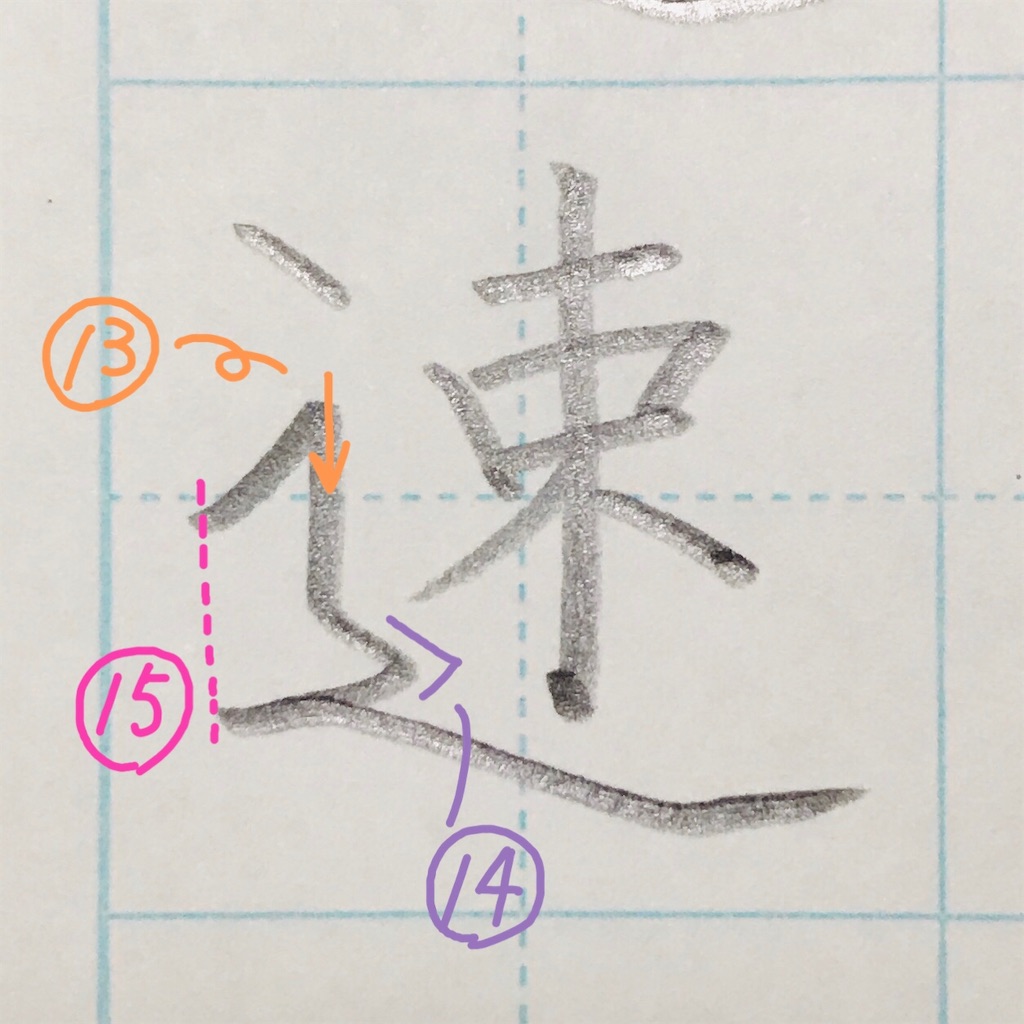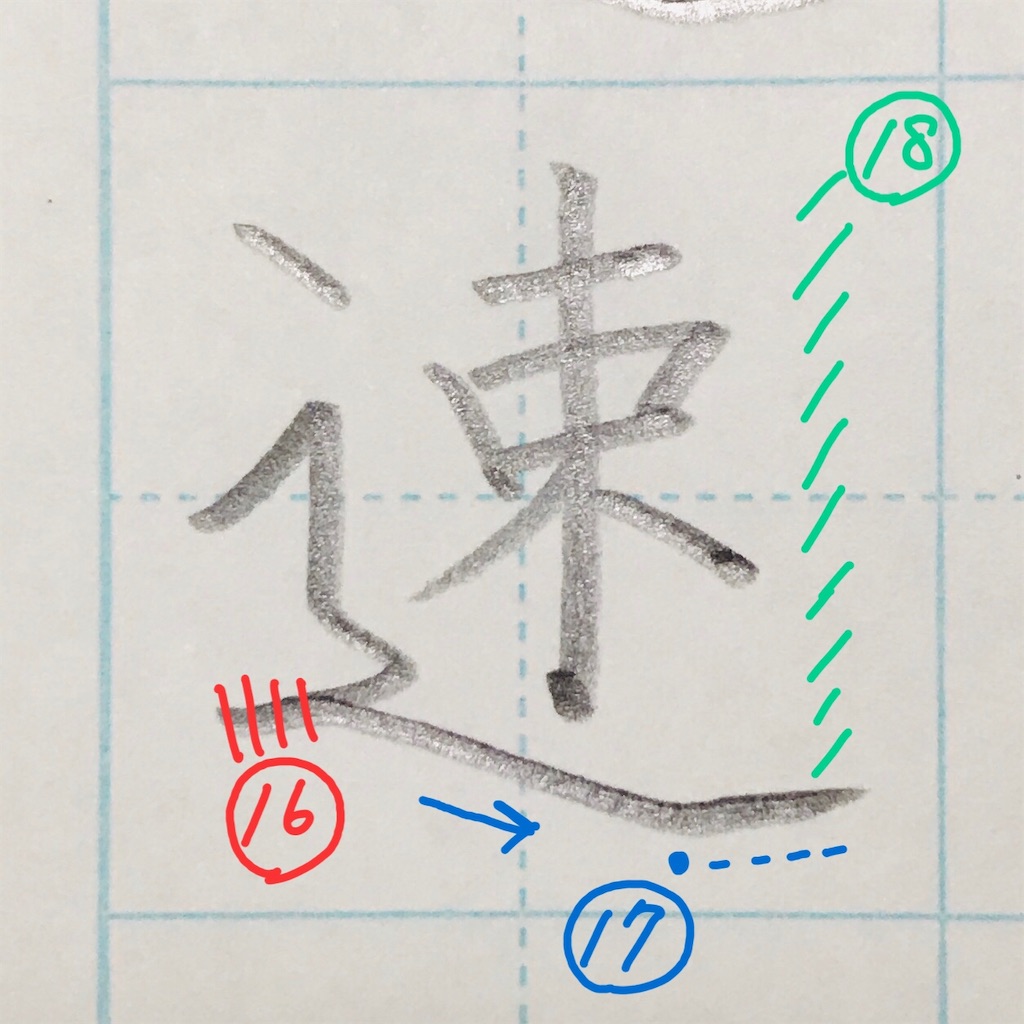
「速」のきれいな書き方。
今回は「速」のきれいな書き方を解説します。
「速」の見本
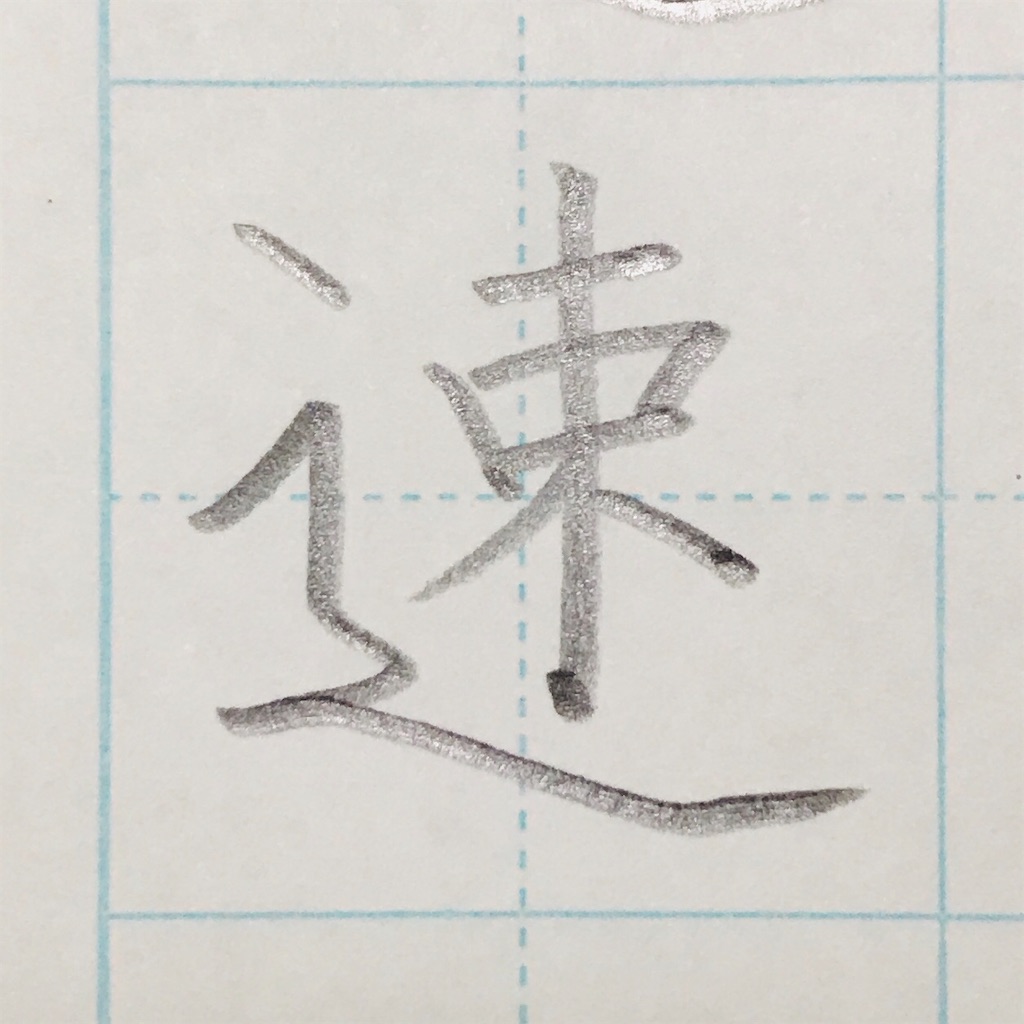
「速」の書き順
10画です。
「速」のポイント
①スタートは中心より少し左から。
②「口」の縦画はキュっと内へ入れる。
③横画は右上がりに揃える。
④間を等しく。
⑤「縦」と「横」を出す。
⑥まっすぐ。「束」部分の中心に。
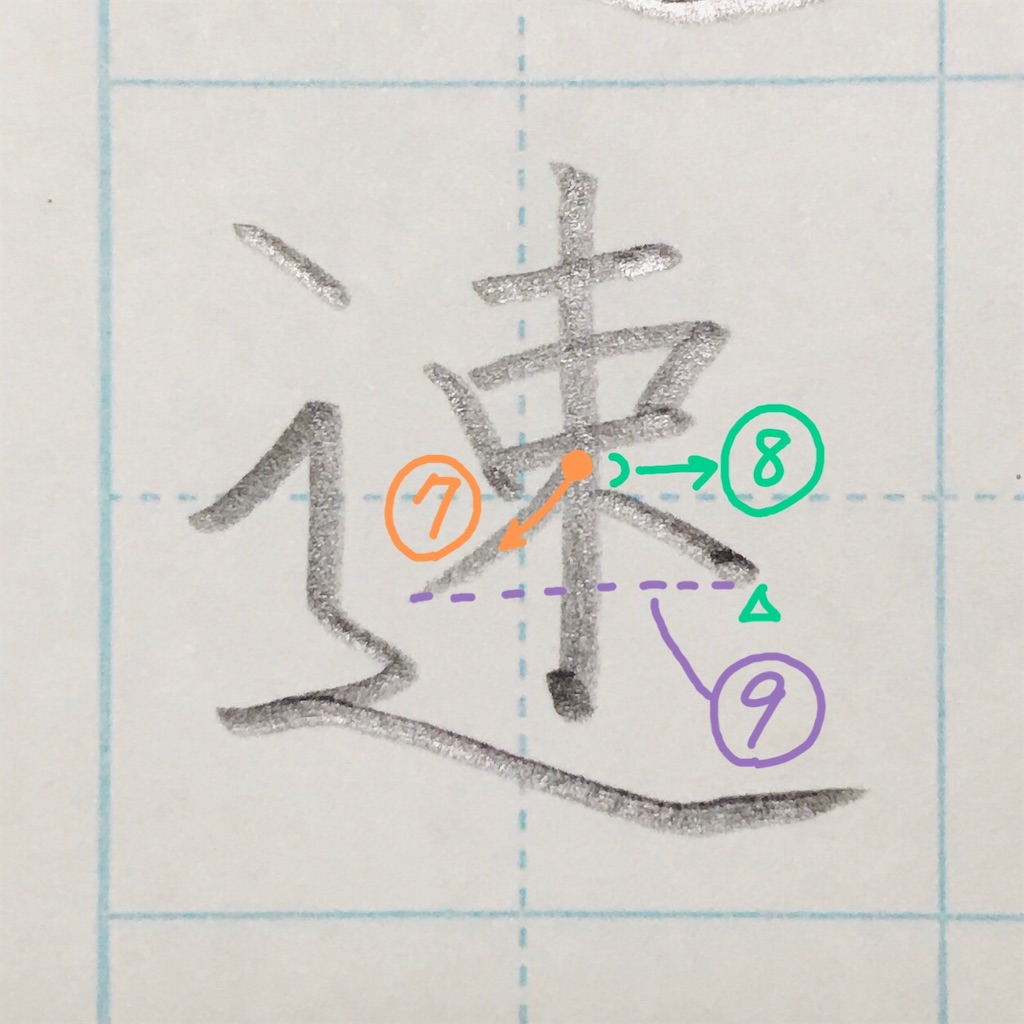
⑦付け根から、45°くらいで払う。
⑧少し空間を空けて、終筆は止める。
⑨左右下を揃える。
さて、ここからは何度も出てきているしんにょうです!
⑩はじめは「束」よりも少し下。
⑪揃える。
⑫ぐいっと右上がりに。
⑬まっすぐ。
⑭右に出す。
⑮左端揃える。
⑯重ねる。
⑰ゆったり下がって、止めて、払う。
⑱「束」がしっかりしんにょうに乗ると◎。
完成!